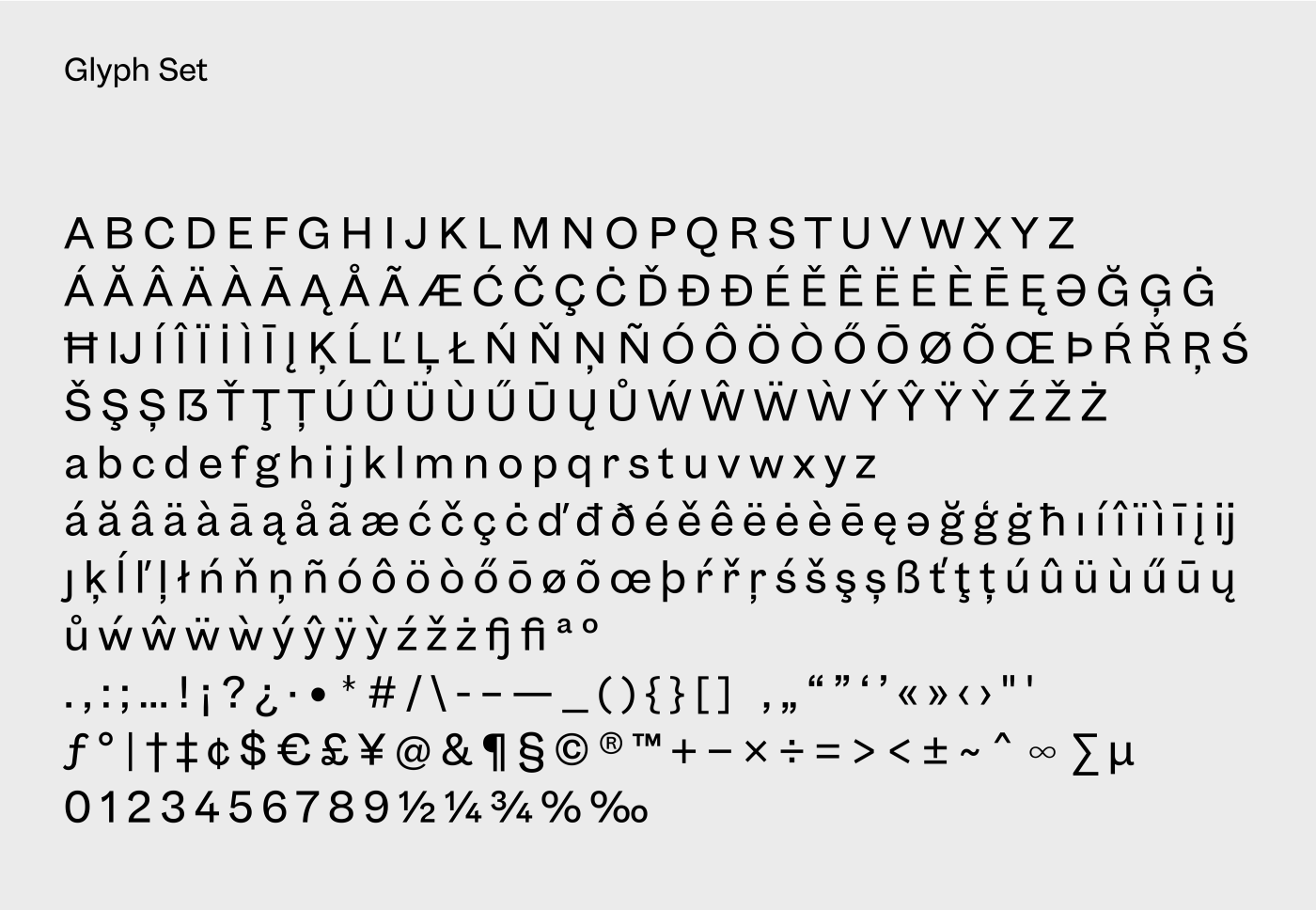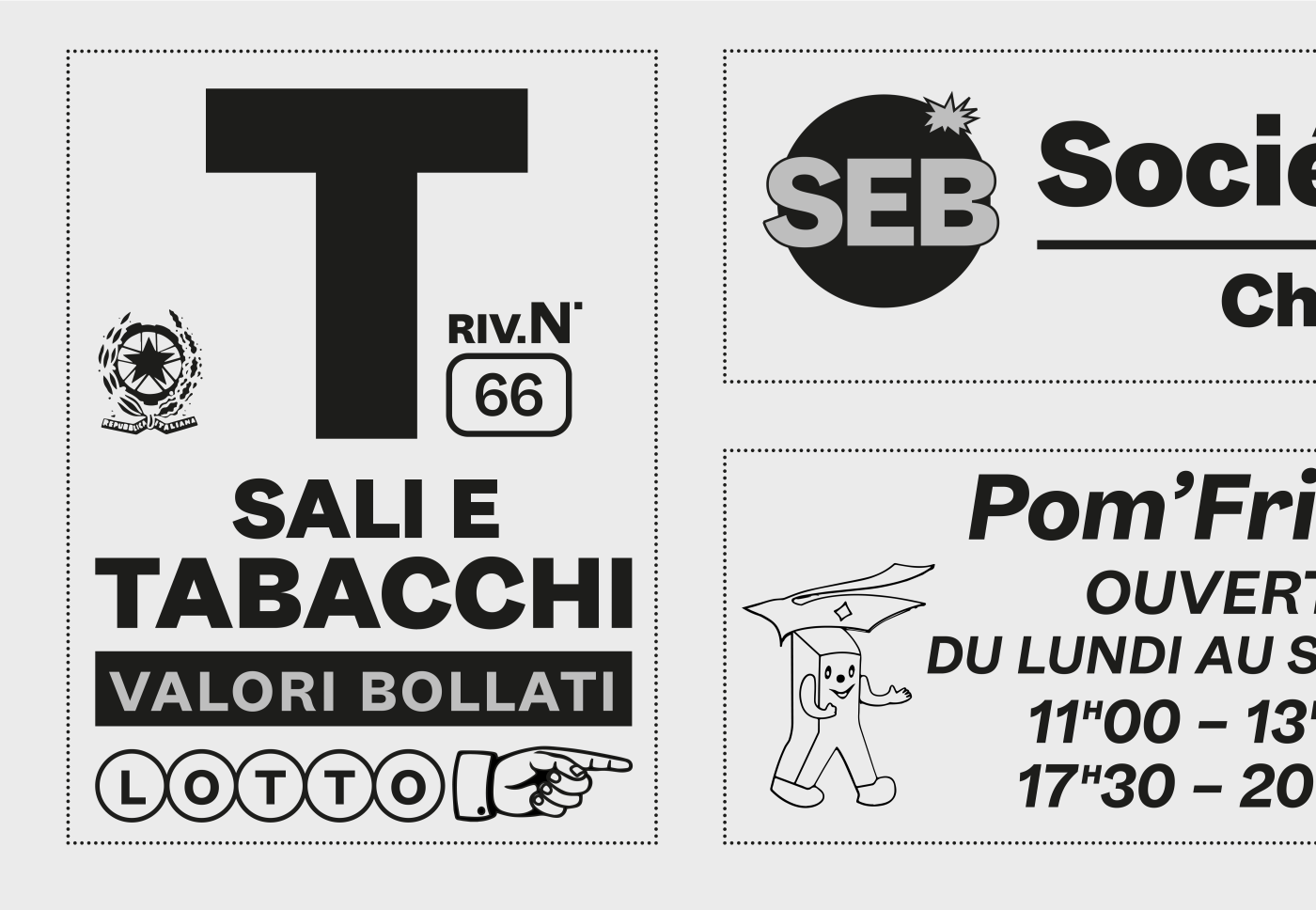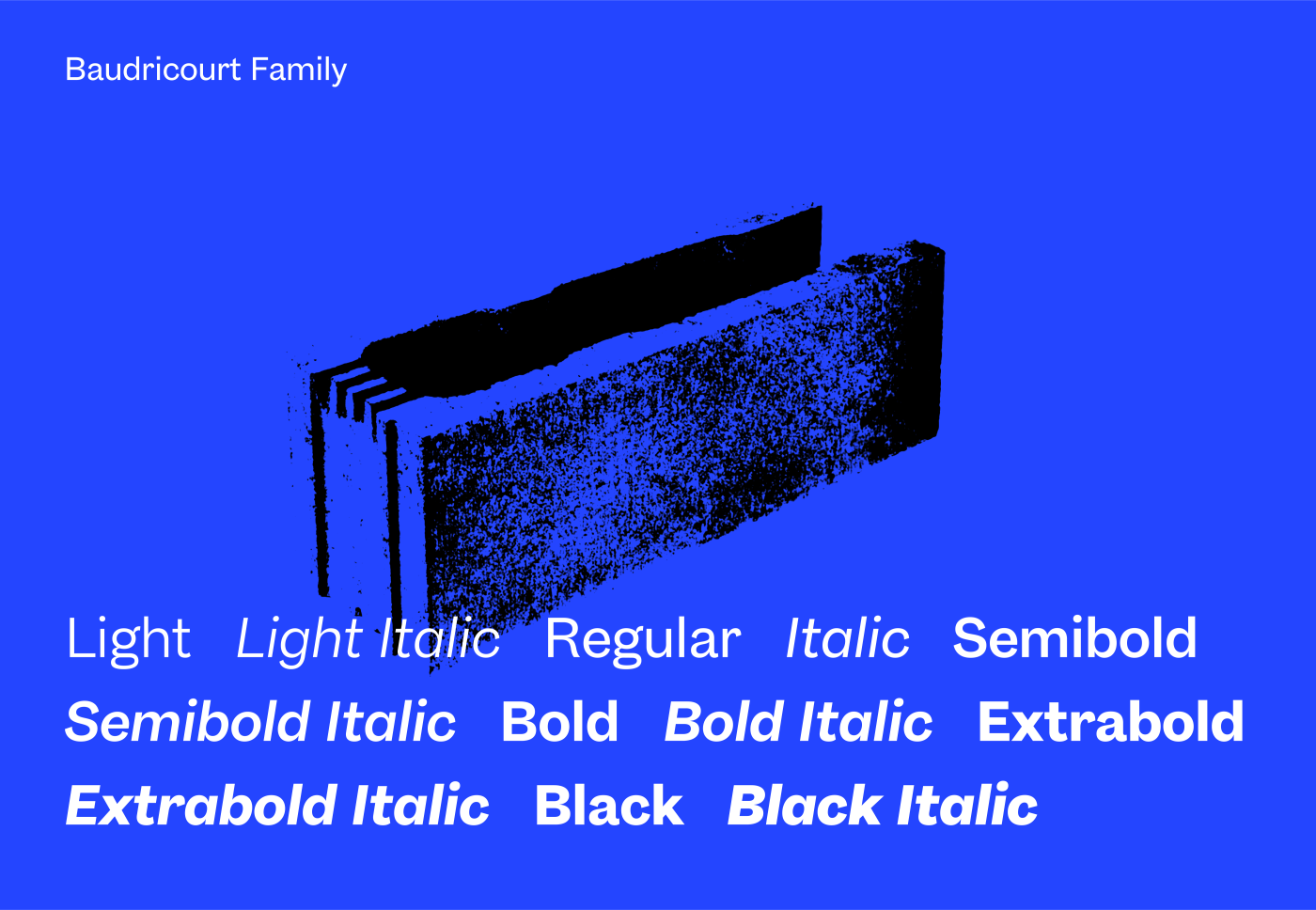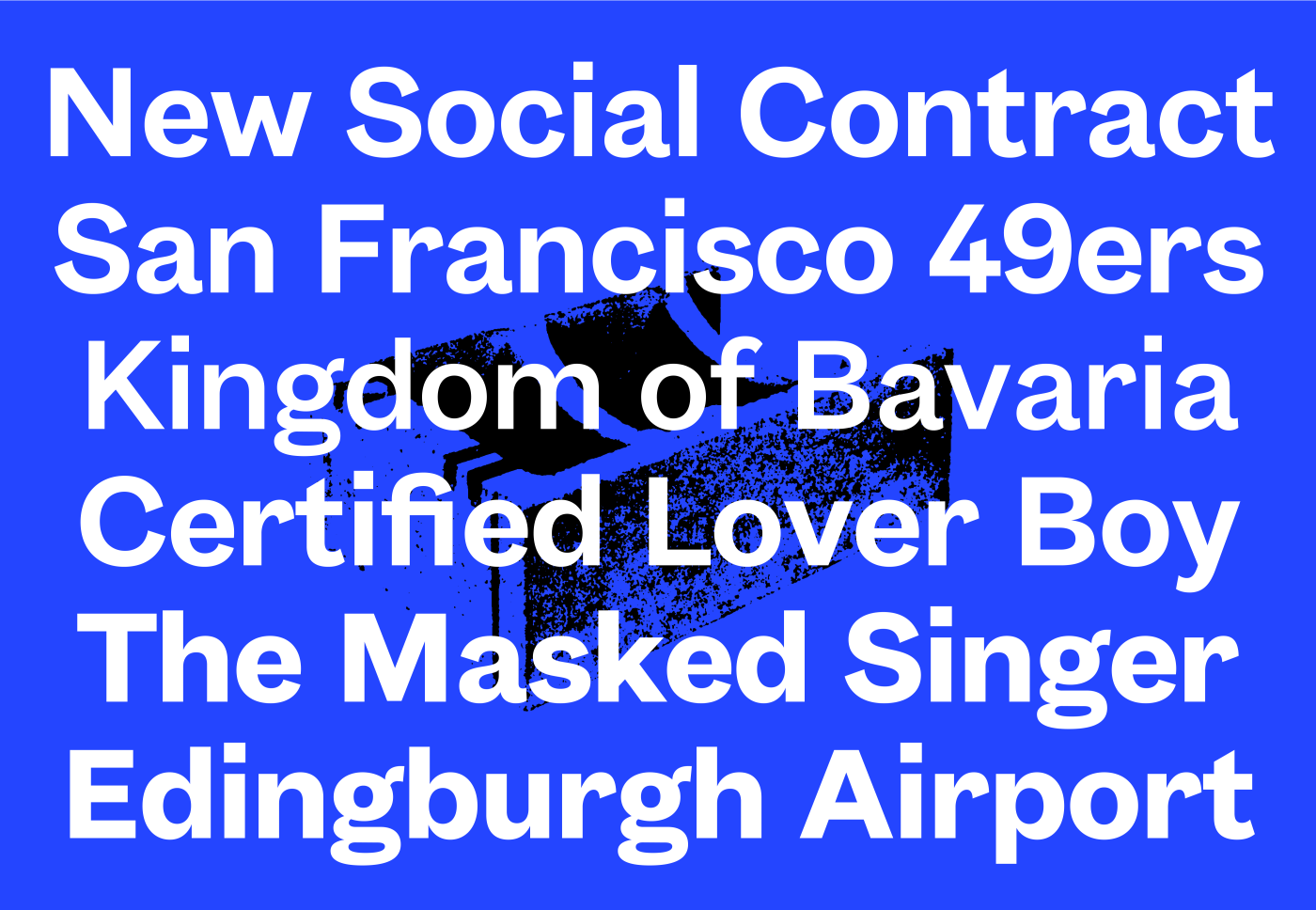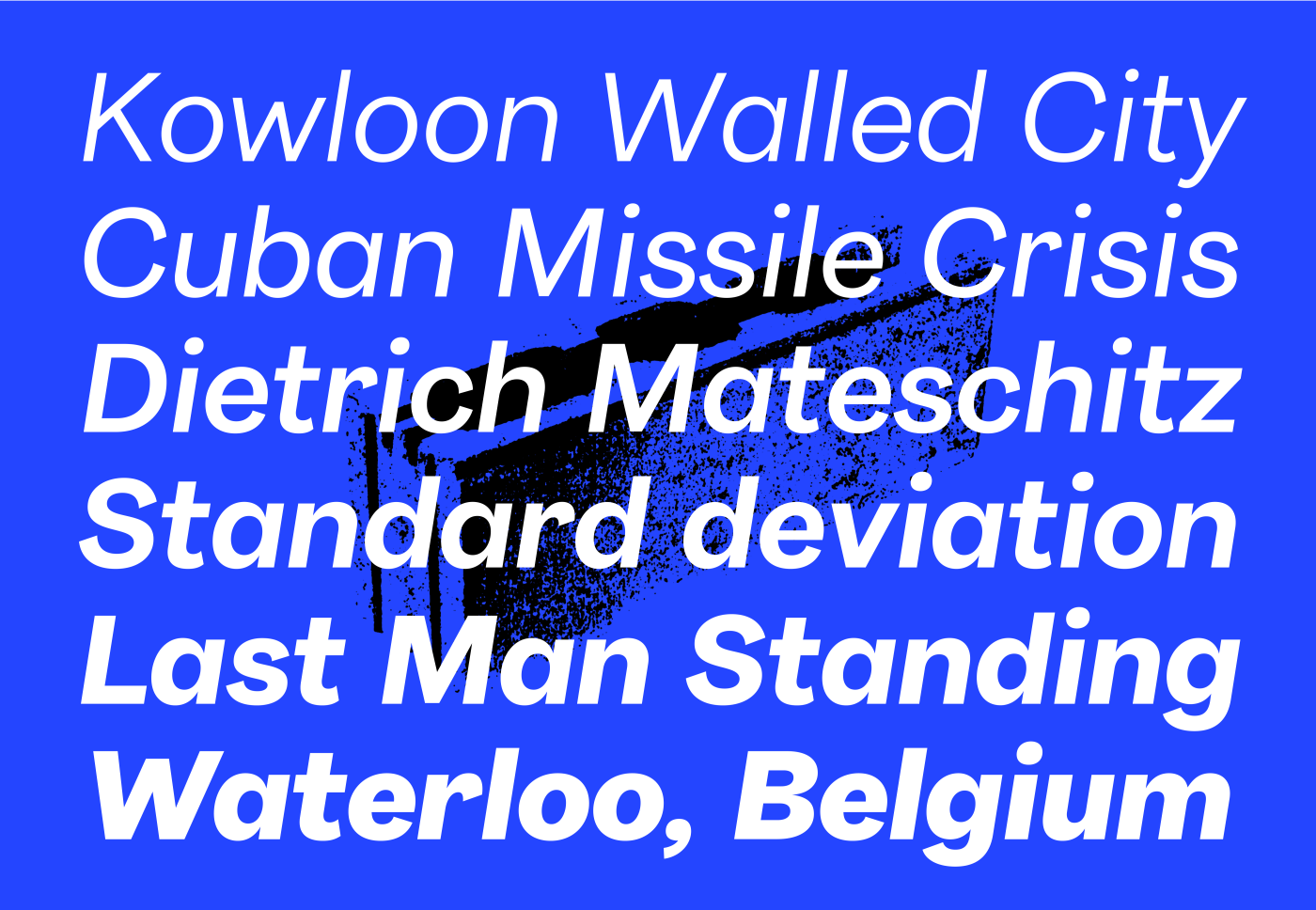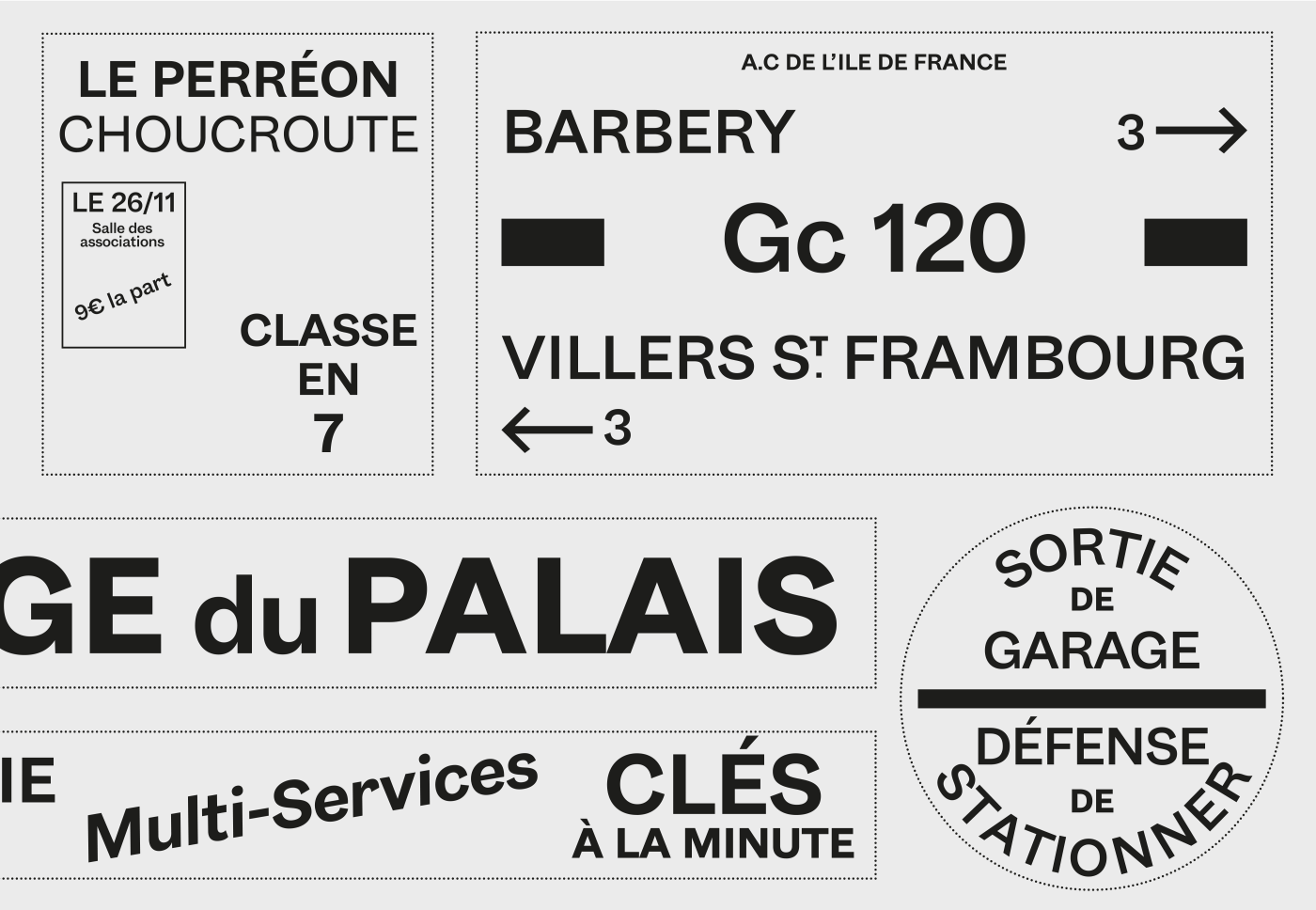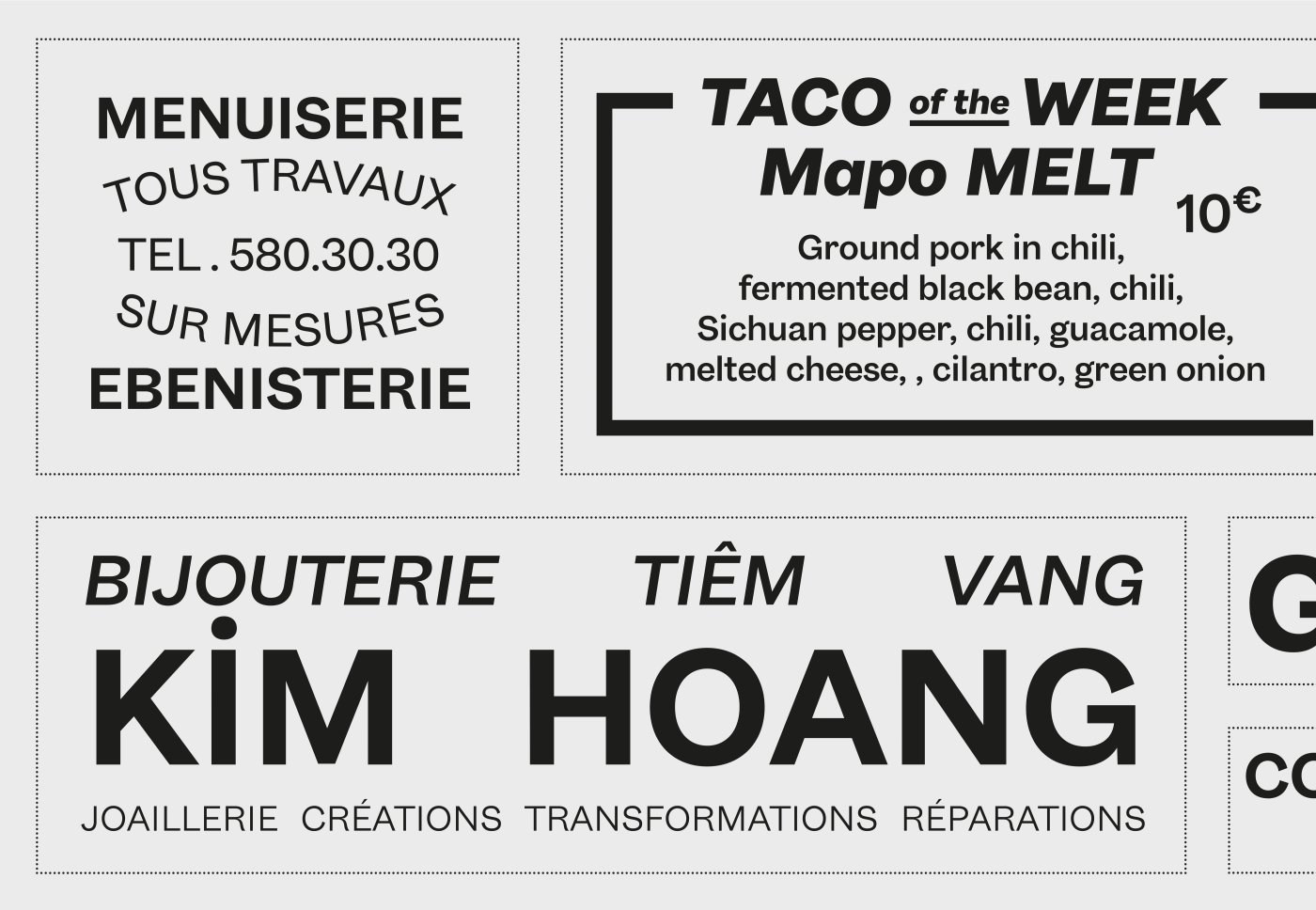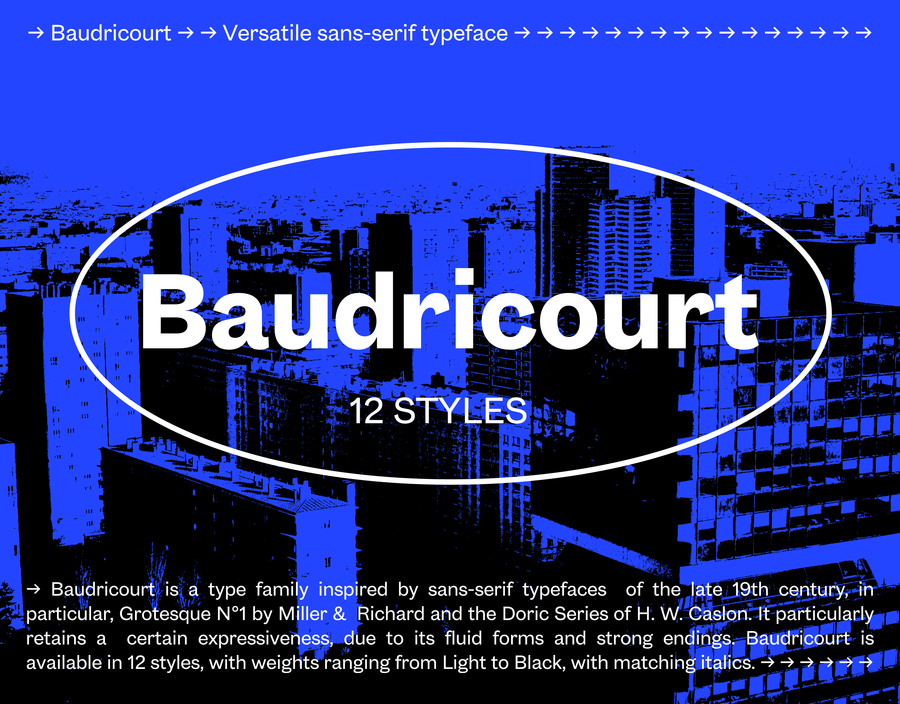
Baudricourt
Baudricourt est une famille de polices inspirée des caractères sans empattement de la fin du XIXe siècle, en particulier Grotesque N°1 de Miller & Richard et la série Doric de H. W. Caslon. Elle conserve notamment une certaine expressivité grâce à ses formes fluides et ses terminaisons marquées.